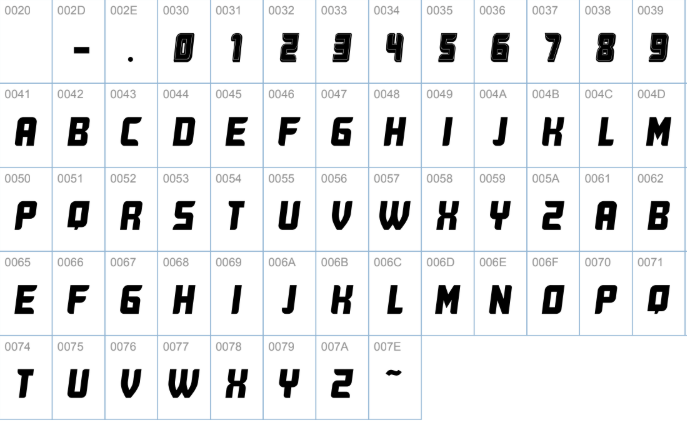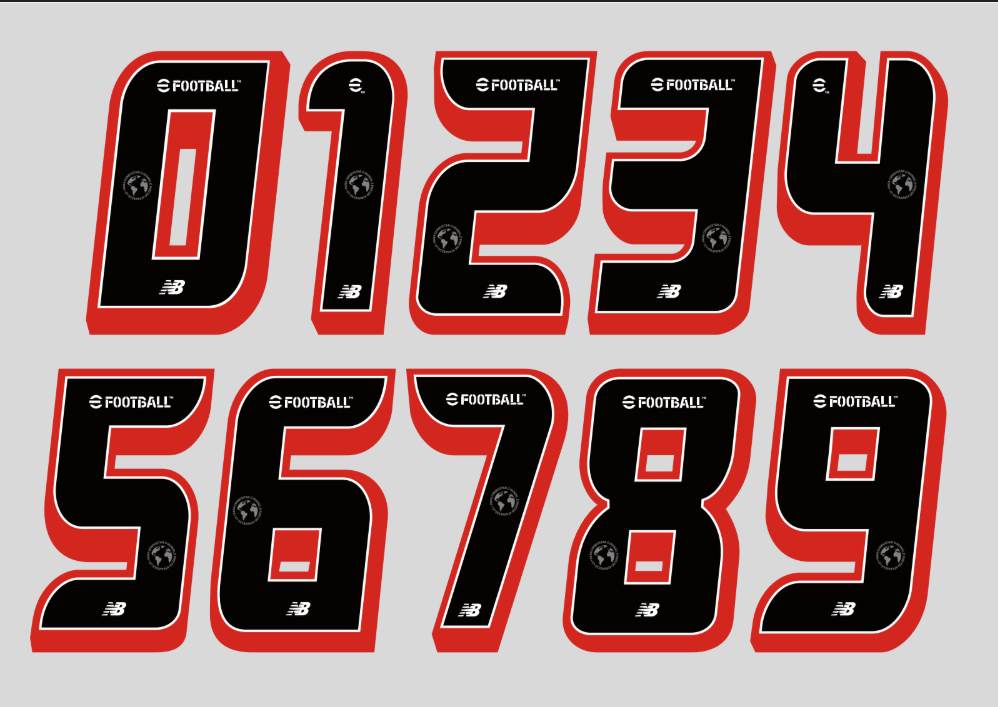
A temporada 2025-2026 do São Paulo FC chegou com uma identidade visual marcante, e a tipografia usada nos uniformes é uma peça central dessa nova estética. Desenvolvida pela New Balance, a nova fornecedora de material esportivo do Tricolor, esta fonte define o visual dos nomes e números que estampam o “Manto Sagrado” nesta temporada.
Se você é designer, entusiasta da personalização ou simplesmente um torcedor apaixonado querendo criar artes incríveis, ter essa fonte é essencial. Ela captura a energia moderna que a New Balance trouxe ao clube, vista nos uniformes de jogo, treino e viagem.
Análise Visual: O Estilo da Fonte
A tipografia da New Balance para o São Paulo FC na temporada 2025-2026 é caracterizada por linhas limpas, modernas e um design ligeiramente “condensado” (estreito), que otimiza a leitura e economiza espaço.
Ela possui cortes angulares e detalhes sutis que transmitem velocidade e precisão, alinhando-se à performance esportiva. É uma fonte robusta, sem ser “pesada”, garantindo excelente legibilidade tanto na TV quanto ao vivo no estádio.
Você verá essa tipografia exata nas costas dos uniformes de todos os jogadores do Tricolor Paulista no Campeonato Brasileiro, Libertadores e demais competições.